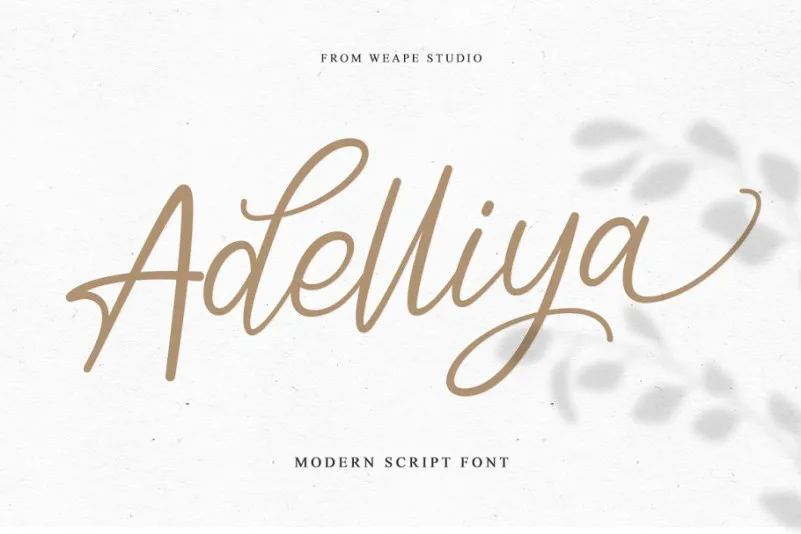
Adelliya Script Font – Download Grátis
Introduzimos a Adelliya Script Font, uma fonte que traz um toque de escrita moderna com estilo tipográfico, útil para enriquecer qualquer texto escrito. Com recursos OpenType e muitos ligados e desenhos à mão finamente ajustados na extremidade, ela torna o resultado parecer como se fosse impresso à mão. Suas várias opções de ligação e desenhos são tão variadas quanto as letras individuais. A Adelliya é perfeita para todos os seus projetos em dia atual e futuro – desde logotipos até embalagens, etiquetas, marcas de água em fotografias, citações, cabeçalhos em blog, cartazes, convites de casamento, material gráfico, letras e até mesmo cartões. É uma fonte que pode se adaptar à qualquer necessidade do seu design, tornando sua criação ainda mais incrível e atraente.